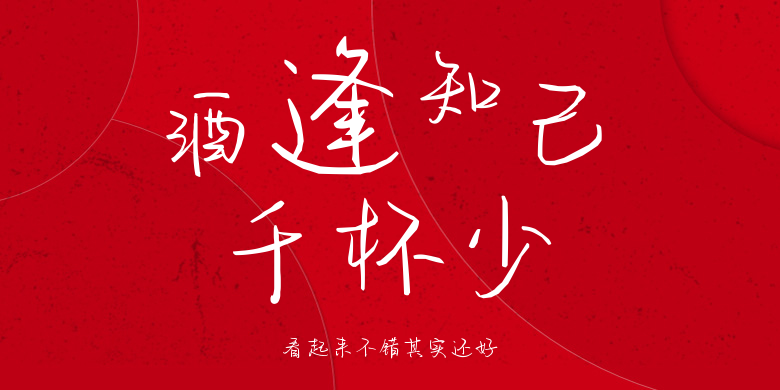
看起来不错其实还好
看起来不错其实还好,这款字体结构工整、笔画清晰,兼顾美观与易读性,适用于标题、正文、海报、包装、LOGO 等多种场景。字形优雅稳定,风格百搭耐看,适配日常排版与创意设计,让文字呈现更舒适、更具质感。看起来不错其实还好一笔一画,皆是细节,以均衡的比例、流畅的线条打造舒适视觉体验,字形端正大气,风格简约现代。无论是商业设计、品牌宣传还是日常排版,都能轻松驾驭,让文字更有格调与力量。看起来不错其实还好字体下载。